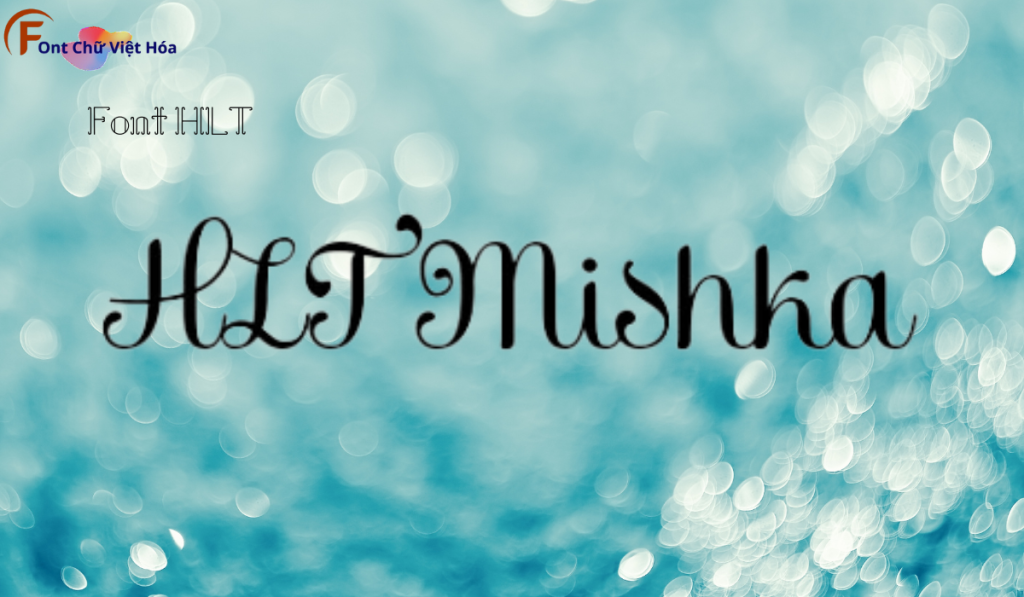
Font HLT Mishka Việt Hóa
Tác giả: HLT
Bộ Font: HLT
Font HLT Mishka Việt Hóa là một font chữ không chân cá tính, thuộc bộ font HLT. Được thiết kế với mục tiêu mang lại sự độc đáo và sáng tạo, font này lý tưởng cho các dự án thiết kế như logo, poster, và bao bì sản phẩm. Với các nét chữ sắc nét và độ dày đều đặn, Font HLT Mishka Việt Hóa không chỉ dễ đọc mà còn tạo cảm giác hiện đại và phá cách. Việc Việt hóa font giúp người dùng dễ dàng sử dụng trong các thiết kế tiếng Việt, mang lại sự tiện lợi và thẩm mỹ cao.